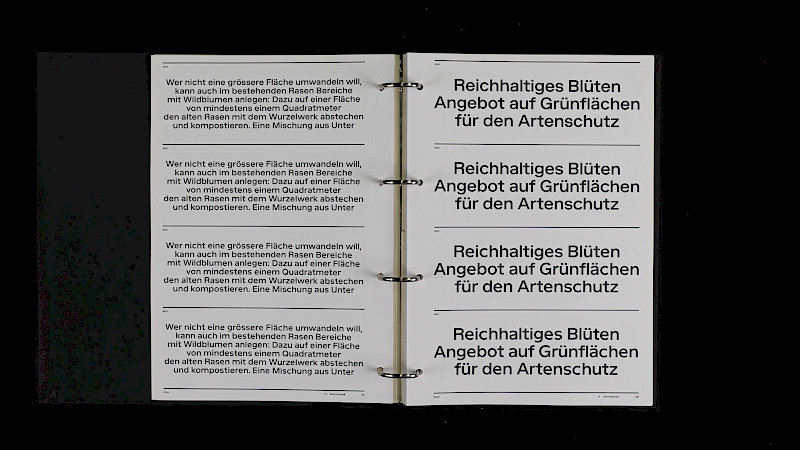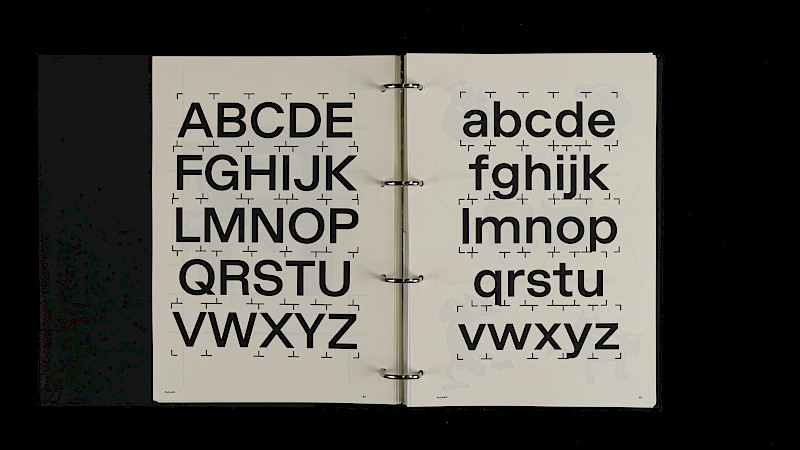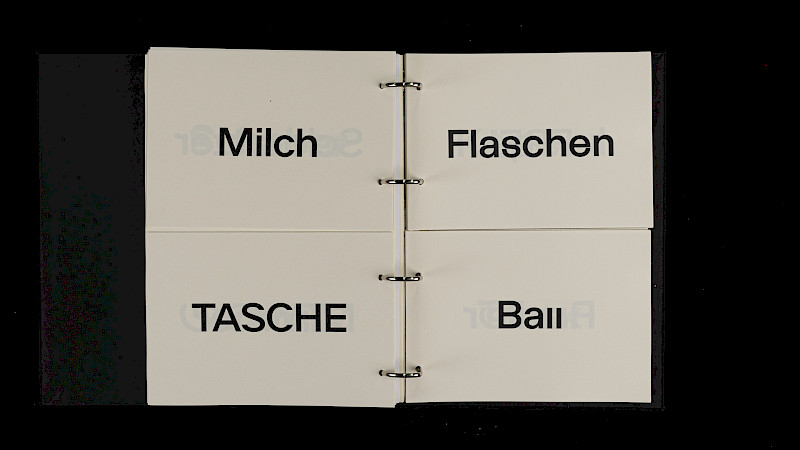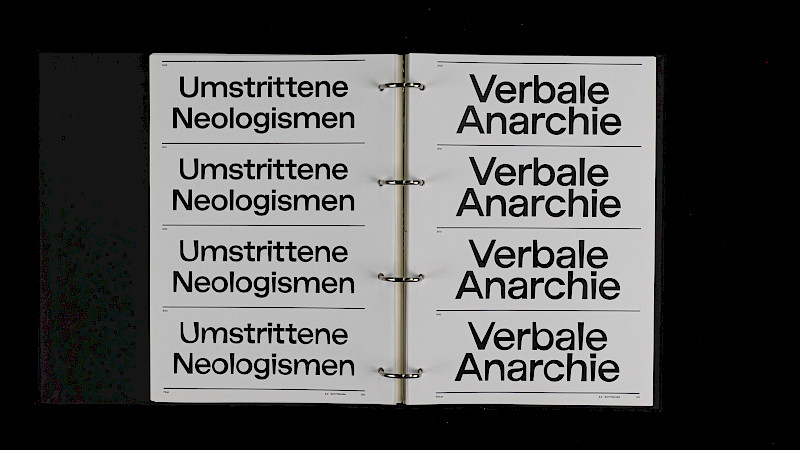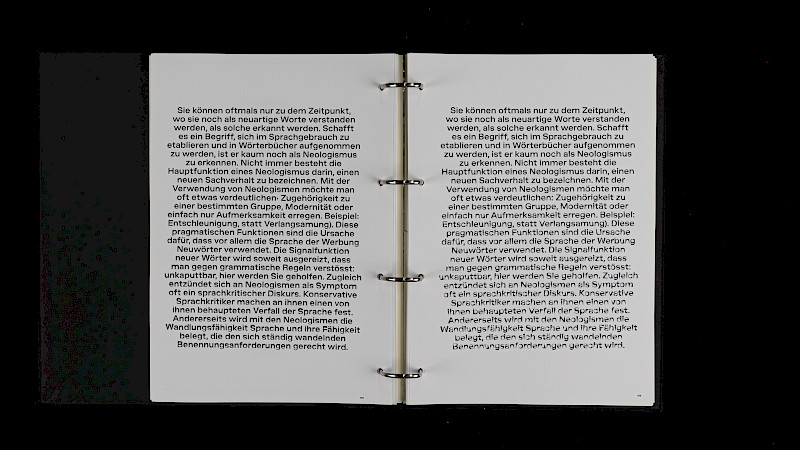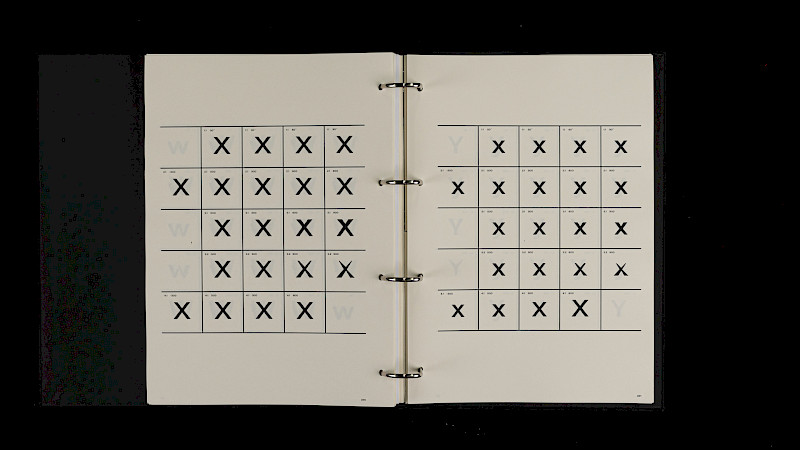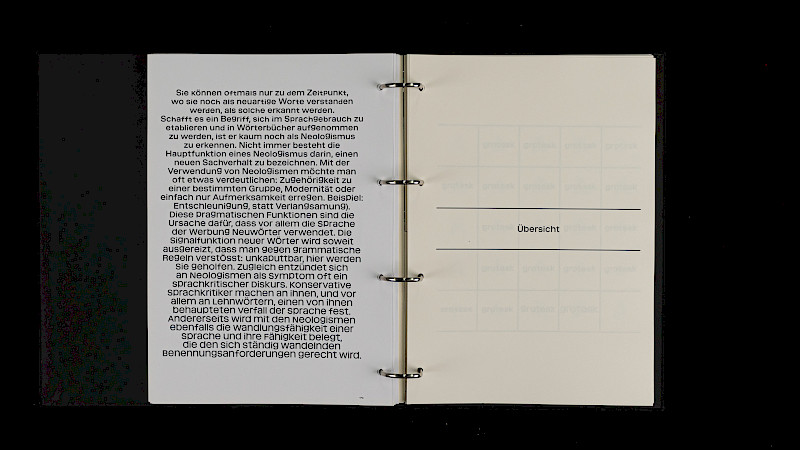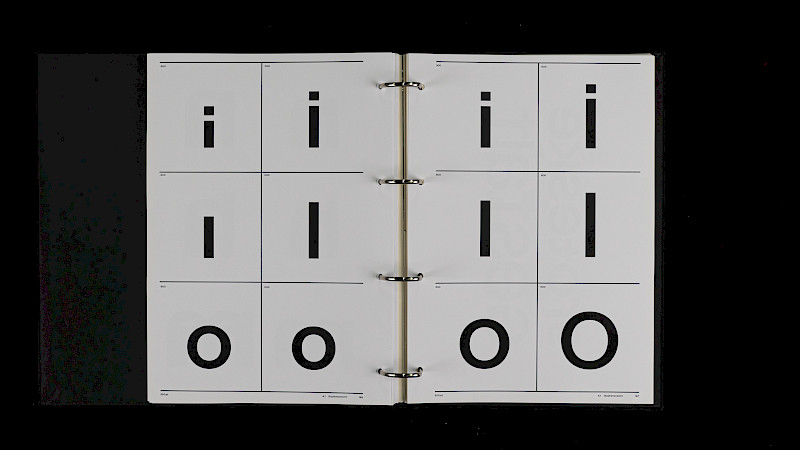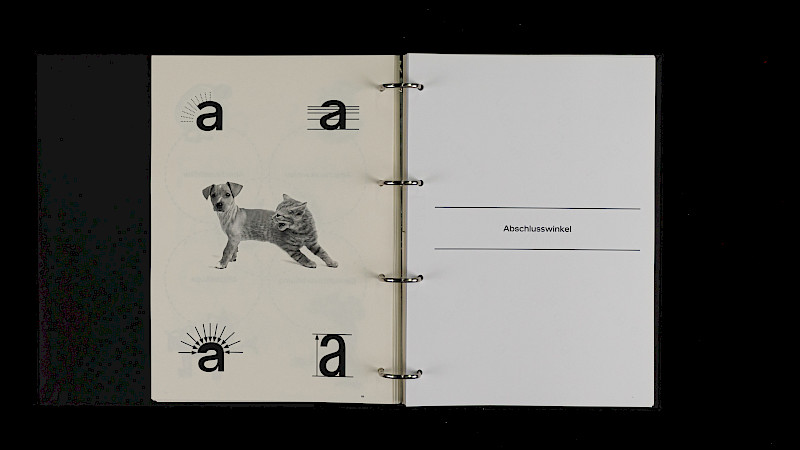
Ursprünglich Grotesk
Diese Arbeit untersucht die Schriftgruppe der «Ursprüngliche Grotesk» aus den späten 1950er-Jahren. Durch ungewöhnliche Kombinationen von technisch-ästhetischen Mitteln, wird nach neuen Ansätzen und Möglichkeiten innerhalb des Gewohnten gesucht.
Groteskschriften haben sich im Laufe der Zeit kontinuierlich an neuen Anforderungen sowie dem technologischen Wandel angepasst. Ursprünglich eine eigenartige Display-Schrift, ist die Grotesk heute ein vielseitiges und oft eingesetztes Mittel der visuellen Kommunikation, dessen Ästhetik dennoch gewöhnlich erscheint. Durch die Übertreibung der untersuchten Mittel wird der notwendige Dualismus geschaffen, der die Bedeutung des “Grotesken” in Frage stellt und die Grenzen zum Normierten aufzeigt